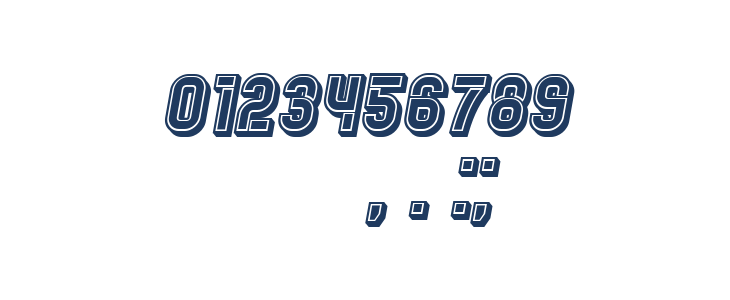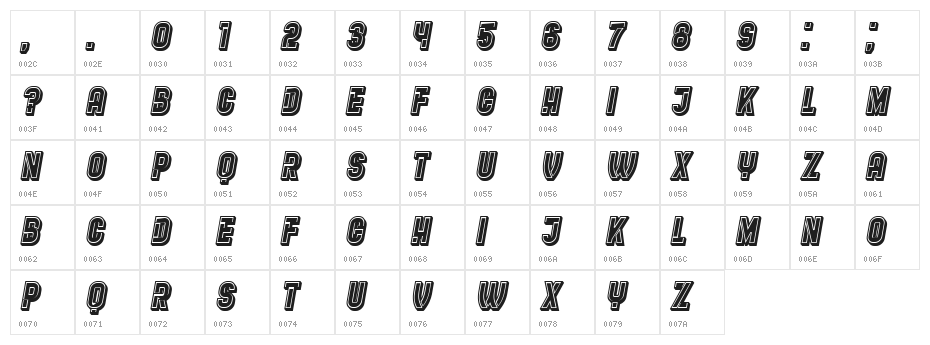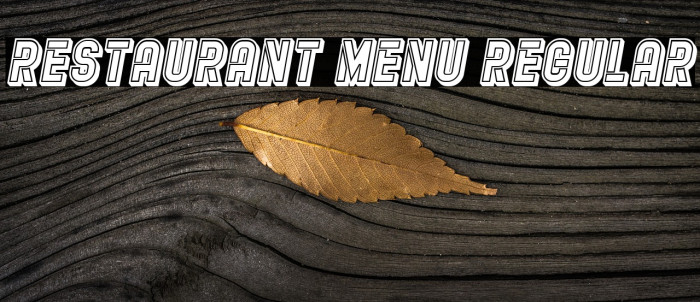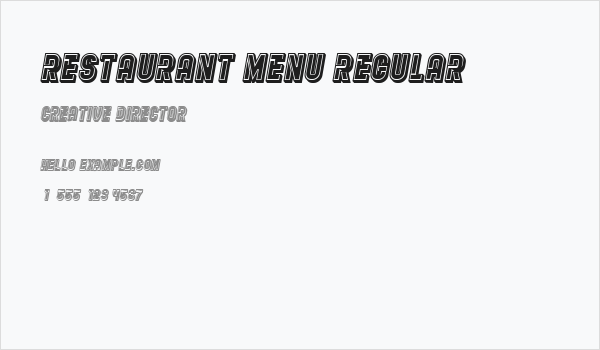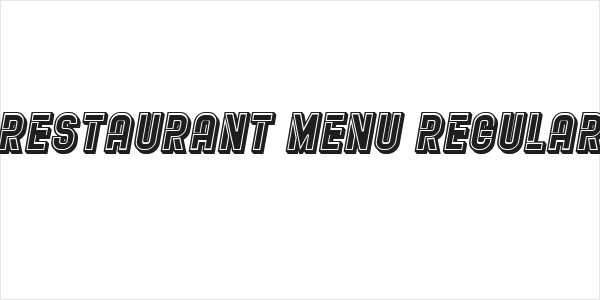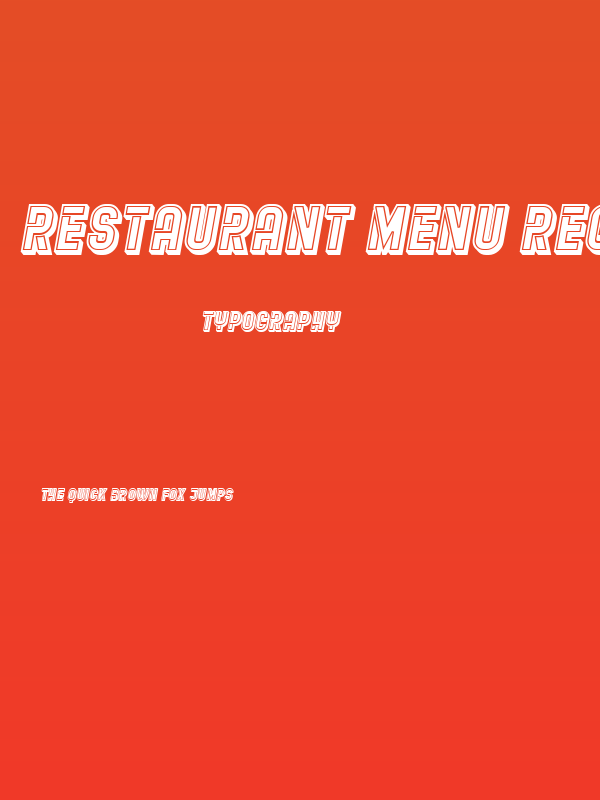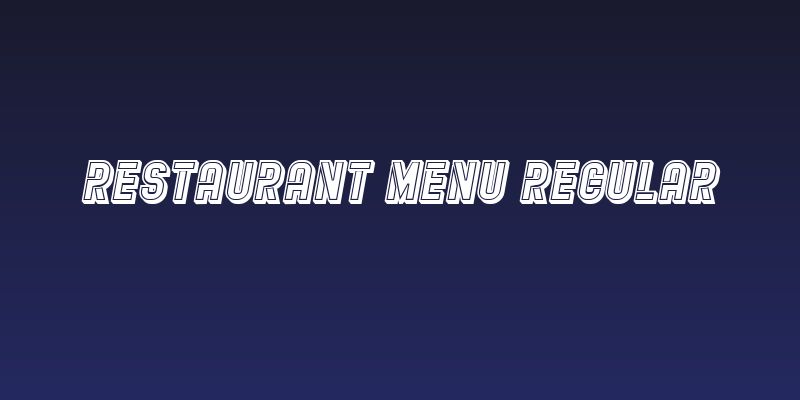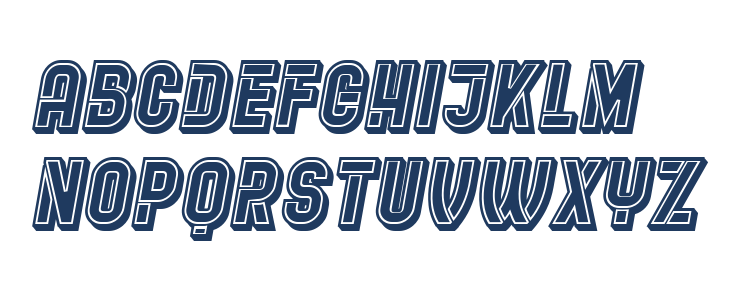
Restaurant Menu Regular Font
| おすすめプロジェクト | Ideal for restaurant menus, posters, event flyers, and branding materials that require a bold and eye-catching design. |